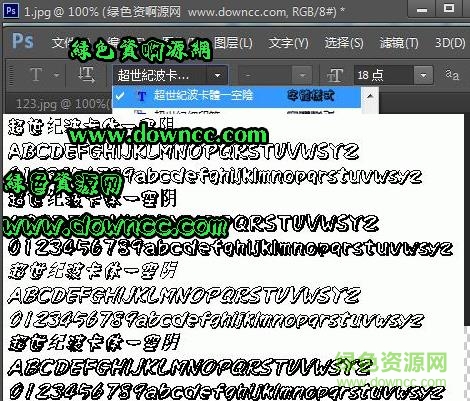
超世紀波卡體一空陰是一款十分有趣的字體樣式,任何文字通過使用這款字體變換后都將產生空心效果,讓你可以運用到包裝設計字幕設計以及文件制作當中運用范圍十分廣泛,需要的朋友就請登陸綠色資源網下載使用吧!
波卡體字體線條粗,筆畫糅合特色十足,應用于橫幅標語、美術設計、宣傳海報、ppt、影視制作以及內容用字等領域還都不錯。